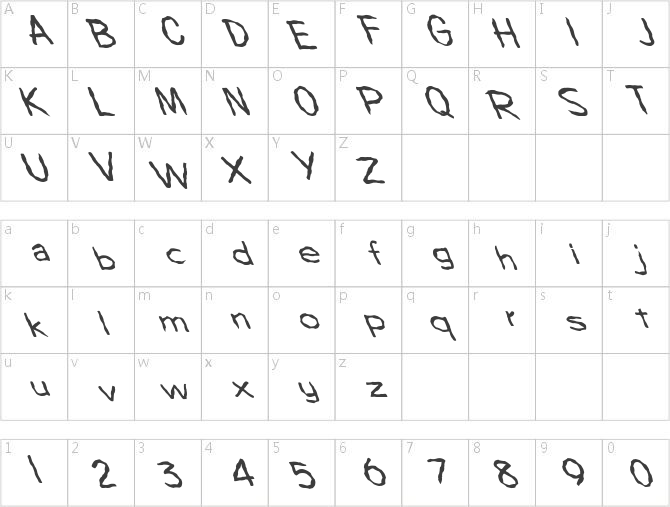
FZ HAND 7 WAVEY LEFTY 詳情頁
FZ HAND 7 WAVEY LEFTY字體字庫是一款讓人賞心悅目、百看不厭的英文字體,適合各類廣告和產(chǎn)品包裝設(shè)計應(yīng)用,字體大小0.07MB,格式為ttf字體,上傳用戶是一直在守護(hù),作者/版權(quán)方為未知